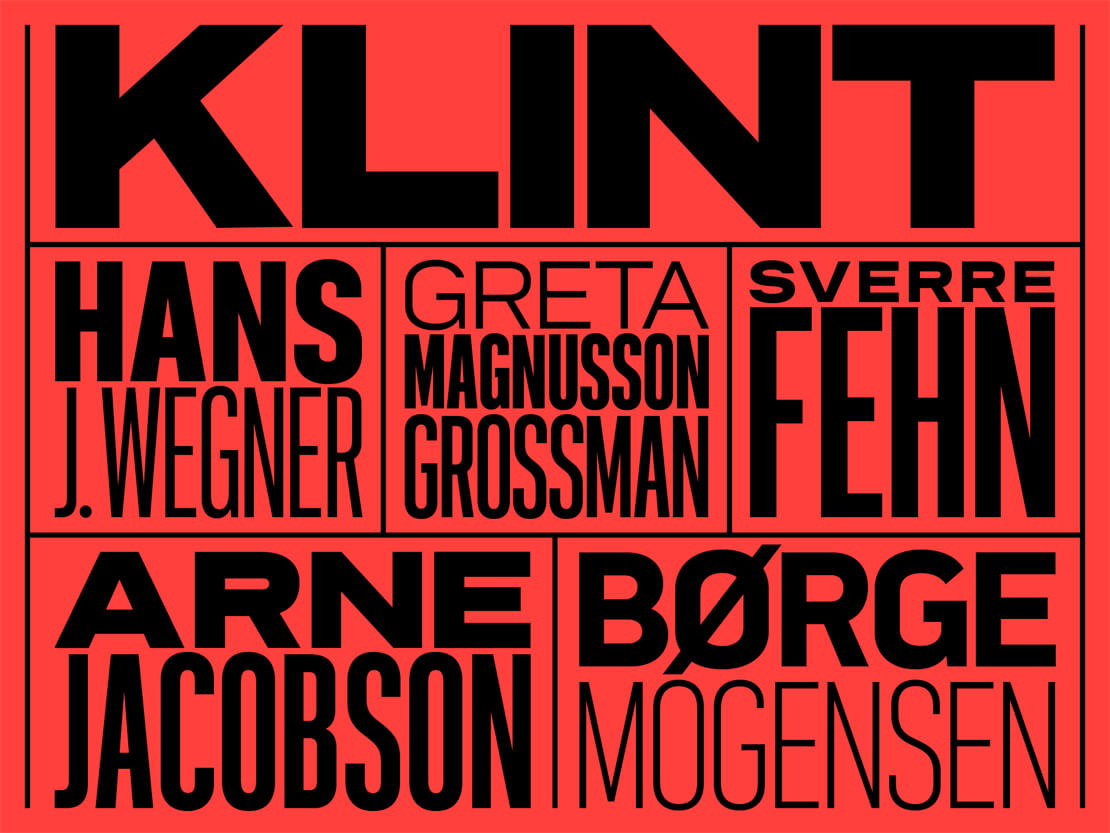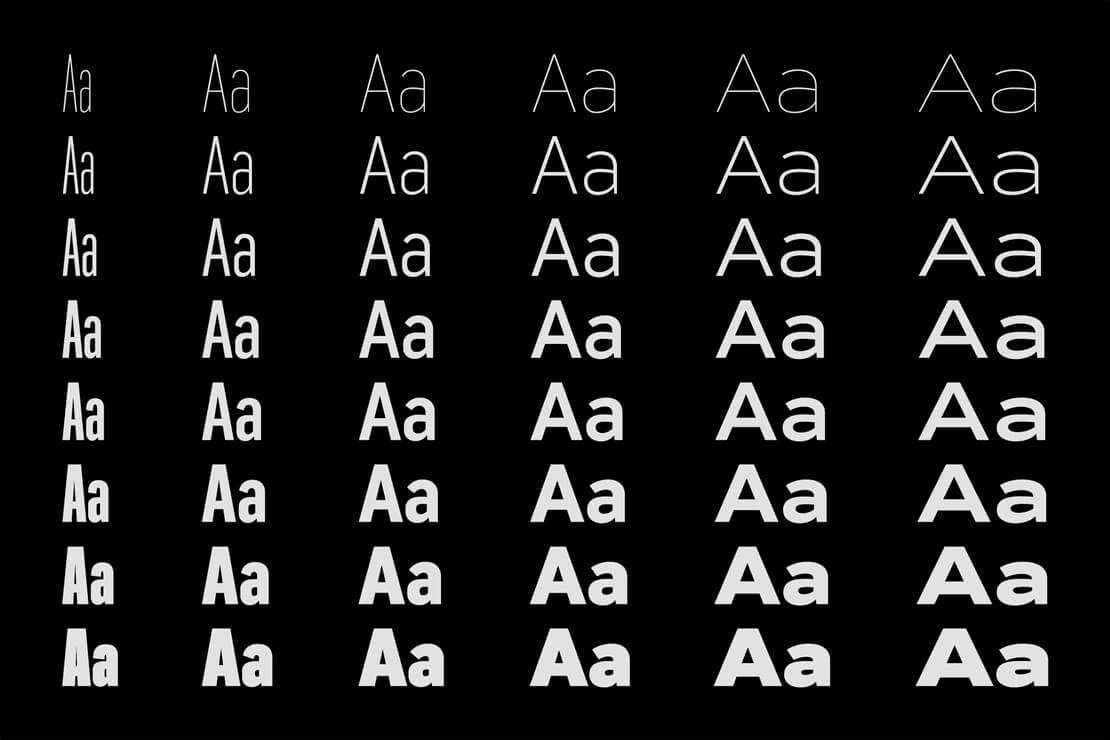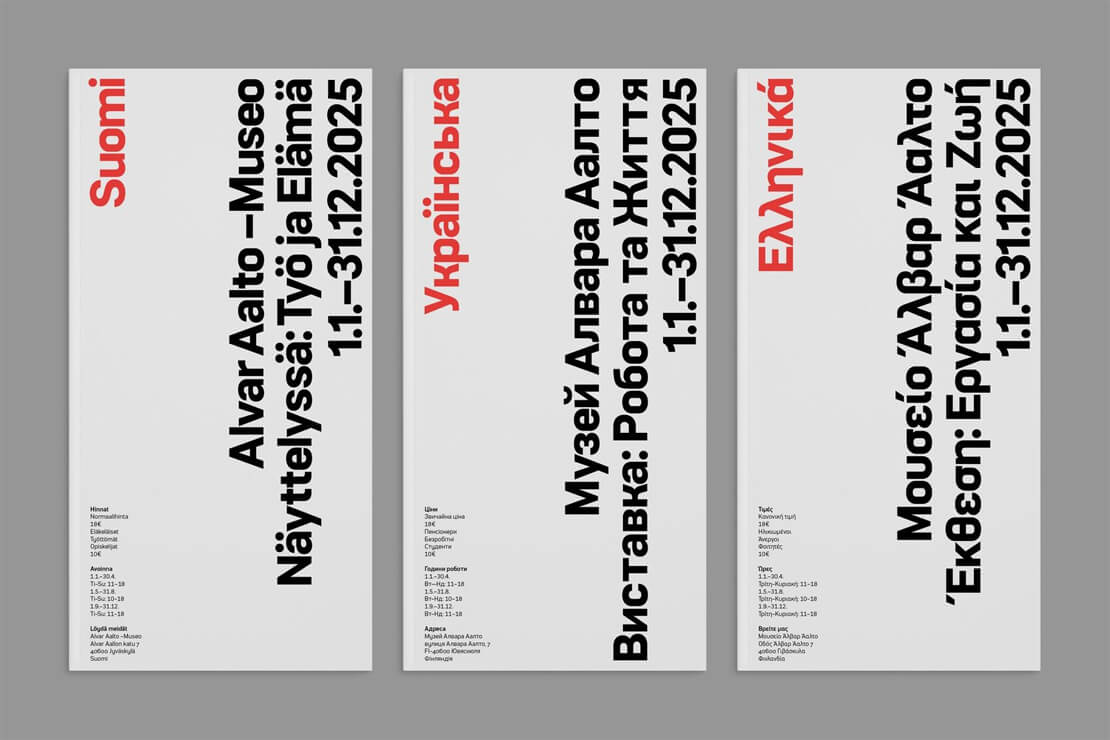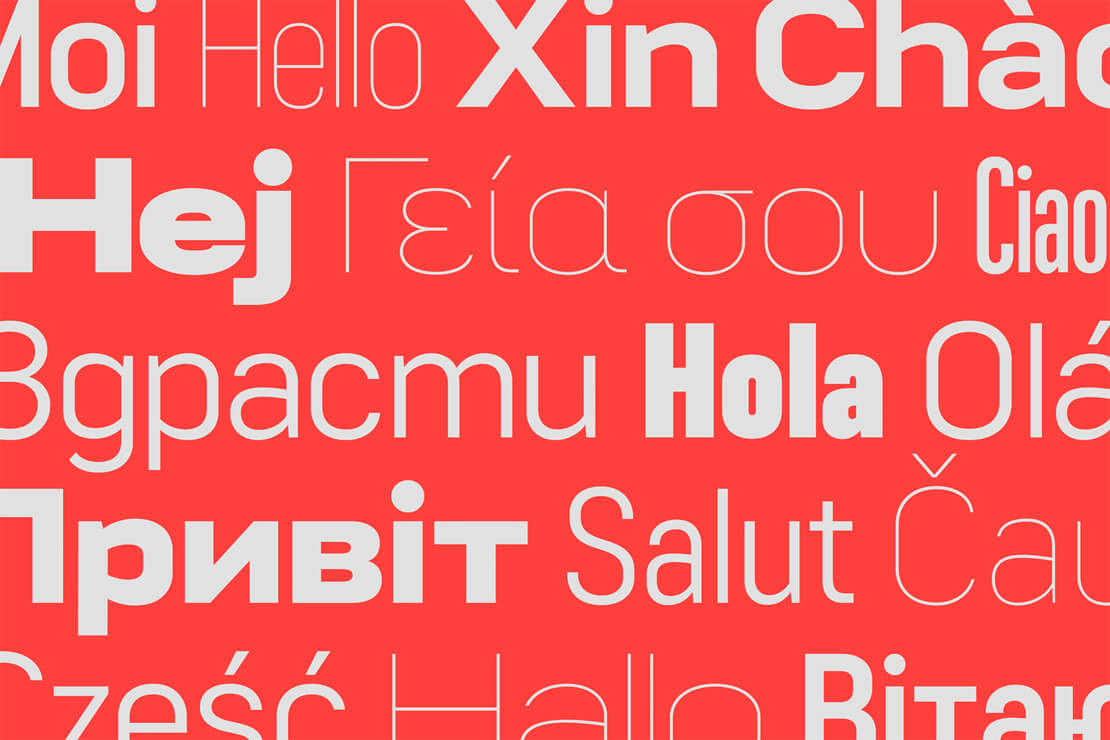
Neue Schriftfamilie »Lintel Next« von The Northern Block
»Lintel Next« ist die weiterentwickelte Version der 2012 erschienenen Lintel und verbindet eine klare, geometrische Konstruktion mit weichen, pillenförmigen Kurven. Die Gestaltung nimmt Bezug auf Prinzipien des finnischen Architekten Alvar Aalto und zielt auf ein ausgewogenes Verhältnis von technischer Präzision und menschlicher Anmutung.
Die Superfamilie umfasst 96 Schnitte: sechs Breiten von »Compressed« bis »Extended«, jeweils in acht Gewichten mit passenden Kursiven. Pro Stil stehen 1.222 Zeichen bereit. Abgedeckt werden Westeuropa, Zentral- und Südeuropa sowie Kyrillisch, Griechisch und Vietnamesisch (Formate: OTF, TTF, WOFF, WOFF2).
Im Zuge der Überarbeitung wurden alle Zeichen neu gezeichnet. Ziel bei der Gestaltung war eine konsistente Lesbarkeit über Größen und Anwendungen hinweg – von Branding über Editorial bis UI – zu erreichen.